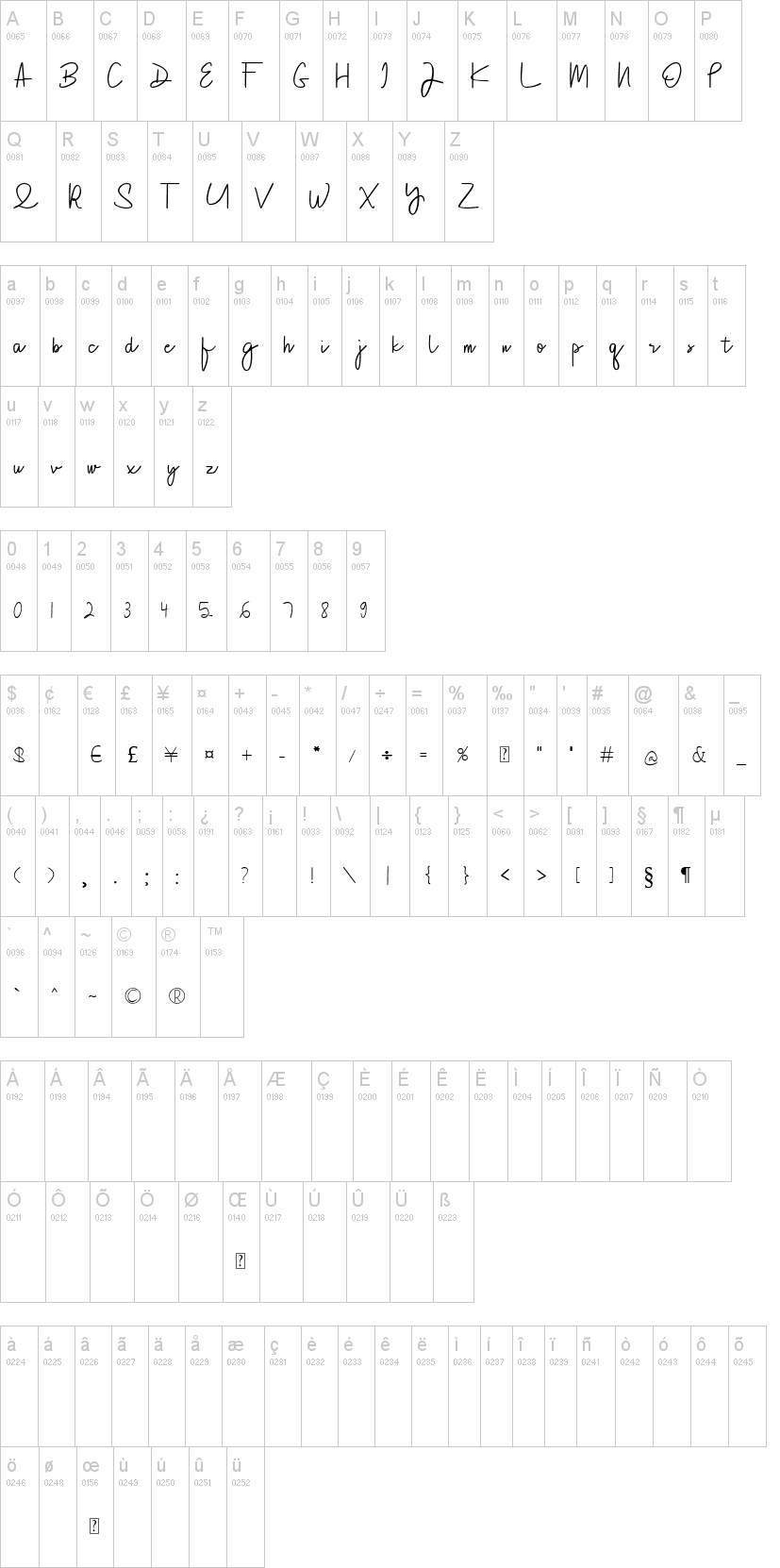
Sevilla 是一种手写风格的字体,主要由英文字母和标点符号组成。它的特点是笔画干净流畅,有一定的装饰性,适合用于标题、贺卡、印刷品等的设计中。Sevilla 字体的风格较为传统,但也蕴含了现代的设计元素,使得它适合用于不同风格的设计项目。该字体的设计者为文化无国界(Cultural Border)工作室,它可以在不同的字体库中找到并使用。内容介绍
Sevilla是一款非常不错的手写艺术字体,具有很好的视觉感,适合于文化类的宣传设计、商业类品牌的广告和产品包装设计以及个性化文字排版等较多场景。